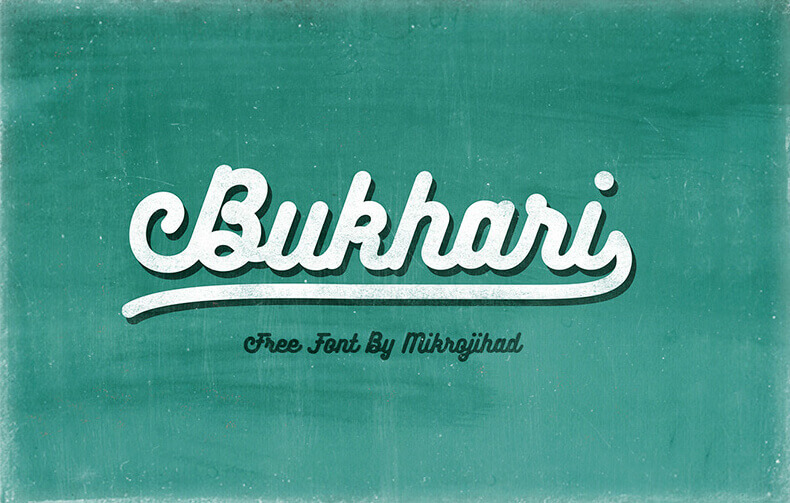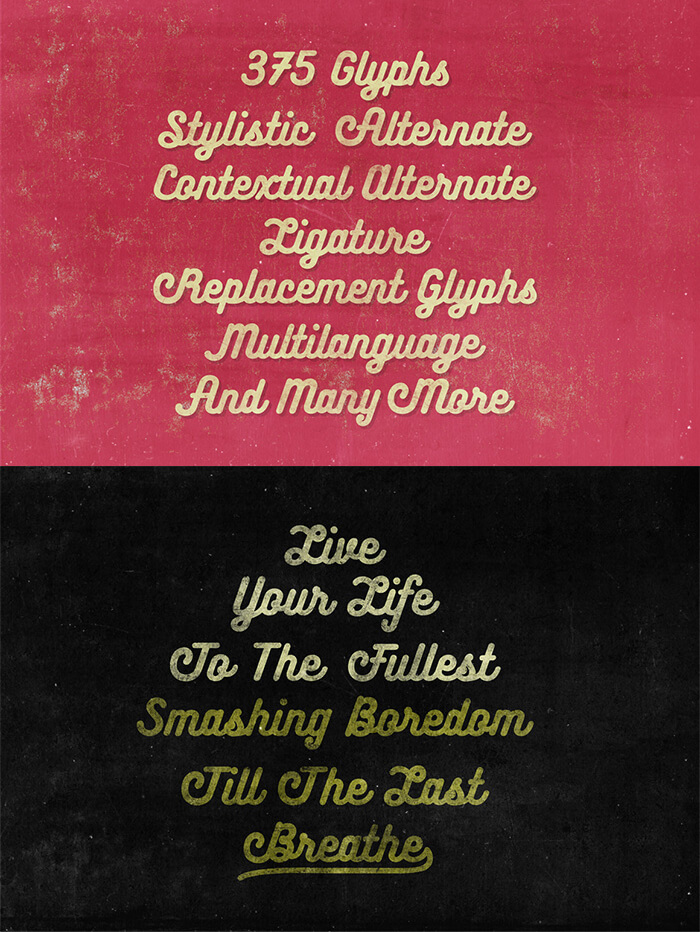
Шрифт - Bukhari
Классный шрифт на латинице с символами похожими на рукописные, имитирующие почерк. Есть два варианта отображения шрифта - обычный и с каллиграфическими завитками. Используйте его в своём дизайне для создания элегантных надписей.